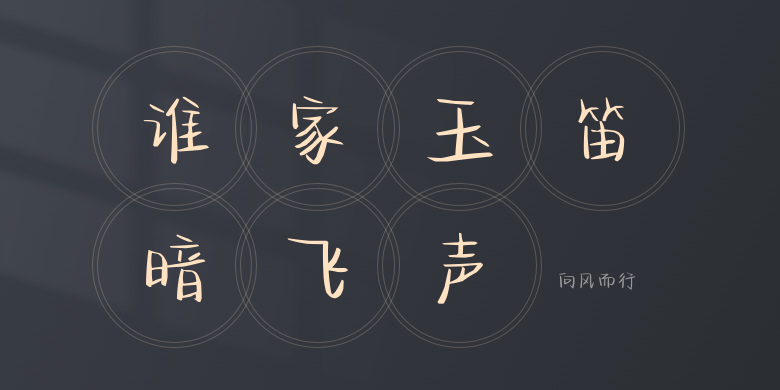
向风而行
向风而行,这款字体结构工整、笔画清晰,兼顾美观与易读性,适用于标题、正文、海报、包装、LOGO 等多种场景。字形优雅稳定,风格百搭耐看,适配日常排版与创意设计,让文字呈现更舒适、更具质感。向风而行一笔一画,皆是细节,以均衡的比例、流畅的线条打造舒适视觉体验,字形端正大气,风格简约现代。无论是商业设计、品牌宣传还是日常排版,都能轻松驾驭,让文字更有格调与力量。向风而行字体下载。